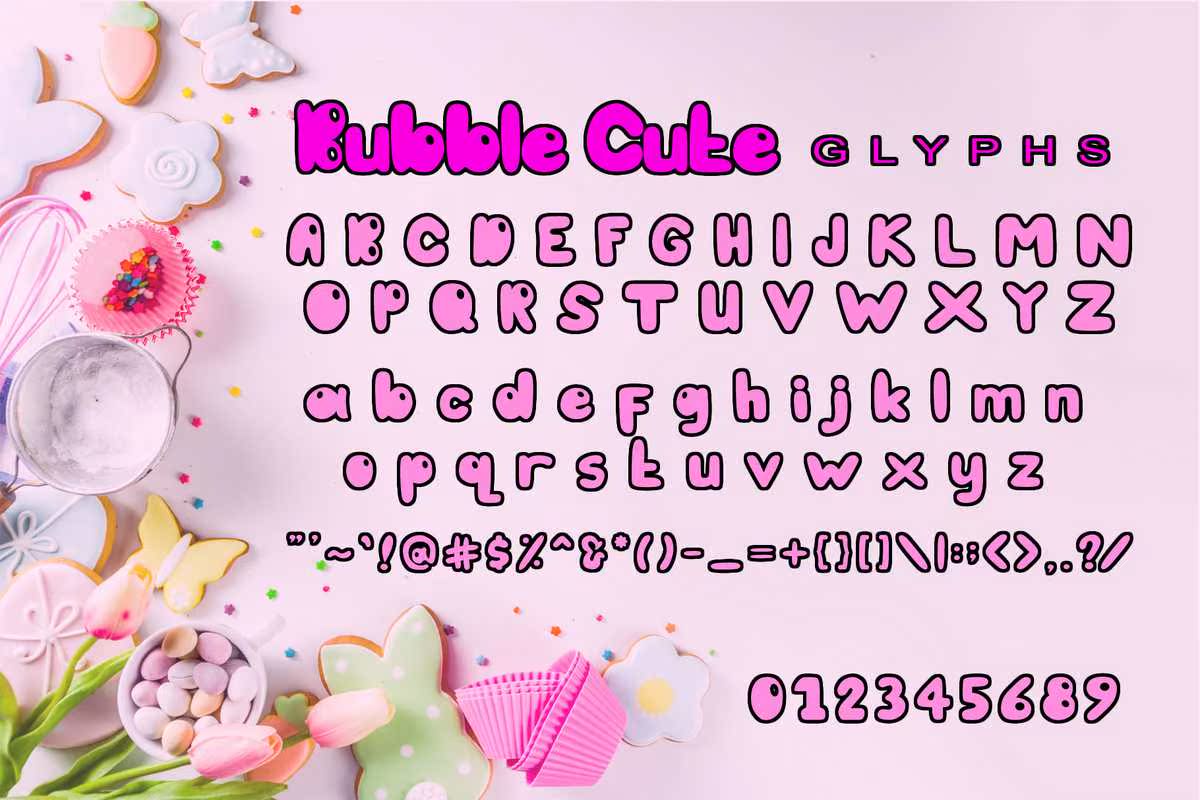
BubbleCute是一款漂亮的字体,精心制作而成,成为用户的最爱。它的偶然性使它看起来非常贴近地球,可读性强,最终用途广得令人难以置信。BubbleCute无论是在繁忙的背景下还是在独立的大标题下,在任何上下文中都会表现出色!BubbleCute是一款漂亮的字体,精心制作而成,成为用户的最爱。它的偶然性使它看起来非常贴近地球,可读性强,最终用途广得令人难以置信。BubbleCute无论是在繁忙的背景下还是在独立的大标题下,在任何上下文中都会表现出色!